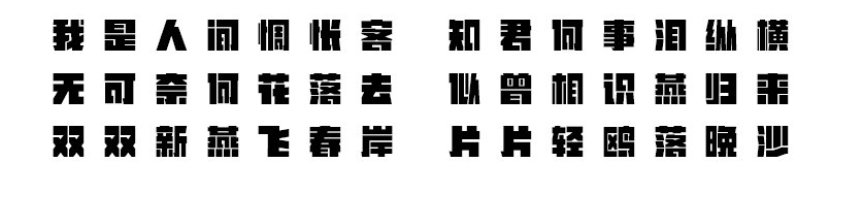
上首金刚体发布
字体名称:上首金刚体
字体类别: 创意字体
适用场景:海报、标题、广告、动漫、影视
上首金刚体简介:上首金刚体,简体中文约6763字,字体笔画加粗,横竖粗细一致,属于无衬线体字体。字体较为刚正,含有坚强不屈,刚正不阿的意味,就如变形金刚般。适用于搭配标志、广告标语、商业广告等高端属性。
上首金刚体预览图展示: